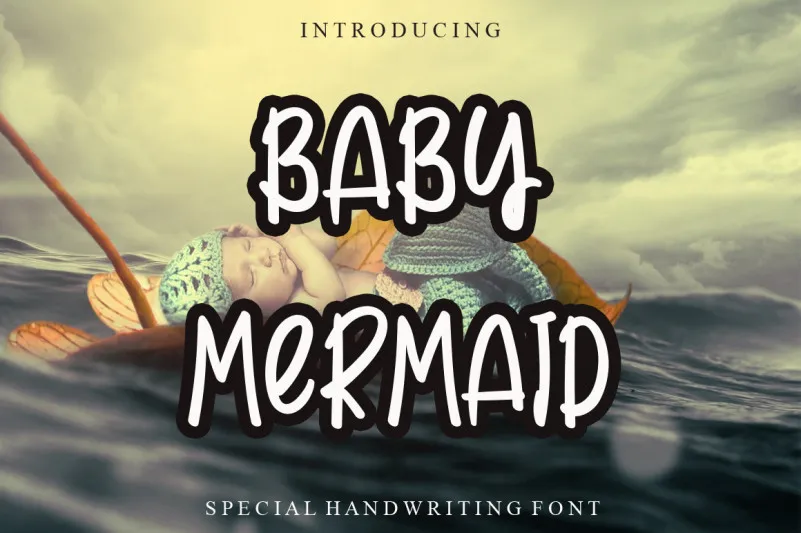
Essa fonte “Baby Mermaid Font” é uma escolha perfeita para aqueles que buscam um estilo descontraído, cool e amigável. Ela é uma fonte escrita a mão adaptada para várias ideias de design, garantindo um toque moderno e elegante em cada projeto. Perfeita para enriquecer layouts digitais com um toque casual e criativo, esta fonte “Baby Mermaid Font” traz à vida qualquer conceito gráfico. Uma opção perfeita para aqueles que querem dar um tom descontraído a seus designs sem sair de uma estética minimalista e sofisticada. Ideal tanto para criar design editorial como para personalizar logotipos, gráficos ou materiais de comunicação digital.